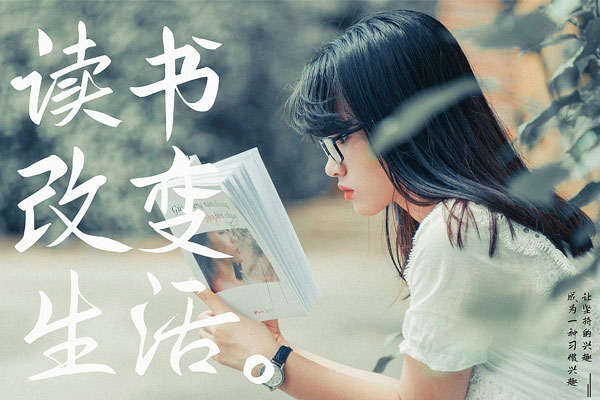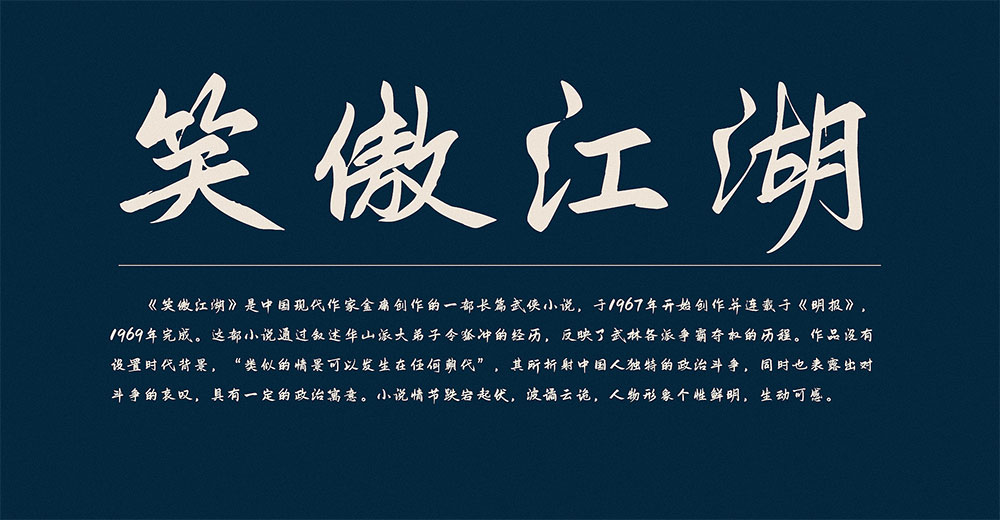
鸿雷板书简体
鸿雷板书简体,一款由泉州设计师鸿雷精心打造的书法字体,于2020年4月发布。若您对这款字体有任何疑问或建议,不妨关注鸿雷的微信公众号“鸿雷字迹”,与作者亲自互动交流。
鸿雷板书简体涵盖了约6800个字符,其字形优雅飘逸,令人赞叹。由于设计师在创作过程中采用了数位板书写,因此将这款字体命名为“板书”。这使得鸿雷板书简体在展现书法韵味的同时,也具备了相当的实用性。
鸿雷板书简体效果预览
鸿雷板书简体字体效果预览